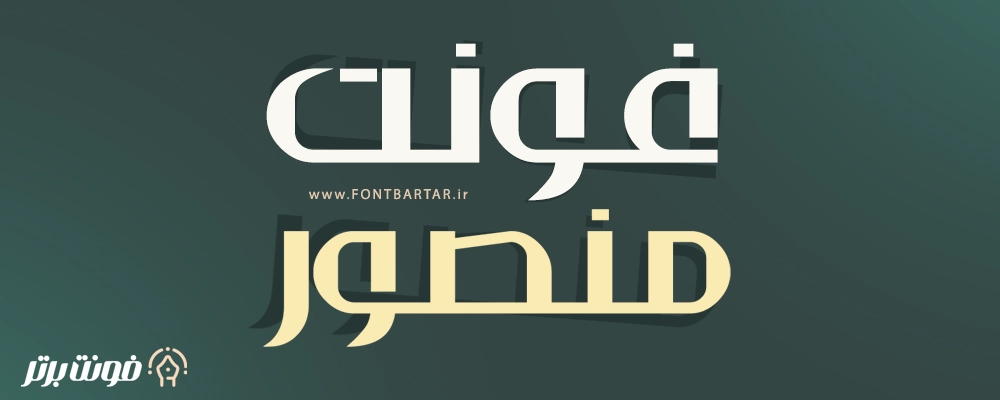
فونت جدید منصور | فونت فارسی شیک و حرفهای برای طراحی
معرفی فونت منصور
فونت منصور یکی از جدیدترین و جذابترین فونت های فارسی است که با طراحی مدرن و در عین حال خوانا، انتخابی عالی برای طراحان گرافیک، تولیدکنندگان محتوا، ناشران و کسبوکارهای آنلاین به شمار میرود. فونت لوگو تایپ فارسی با الهام از سبکهای مینیمال طراحی شده و ترکیبی از زیبایی، کاربردی بودن و نوستالژی مدرن را در خود جای داده است.
اگر به دنبال یک فونت فارسی حرفهای برای لوگو، پوستر، بنر تبلیغاتی، موشن گرافیک یا وبسایت هستید، فونت زیبا منصور بهترین گزینه برای شماست.
ویژگی های فونت منصور
- فونت لوگوتایپ طراحی مدرن و کاربردی
- مناسب برای لوگوتایپ و برندینگ
- وضوح بالا در نمایشگر و چاپ
- قابل استفاده در طراحی پوستر، جلد کتاب، وبسایت و شبکههای اجتماعی
چرا فونت جدید منصور بهترین انتخاب است؟
لوگوتایپ فارسی فونت منصور علاوه بر زیبایی بصری، از نظر سئو و تجربه کاربری نیز اهمیت زیادی دارد. استفاده از دانلود فونت فارسی در طراحی سایت یا محتوای بصری میتواند باعث افزایش نرخ کلیک (CTR) و جلب توجه کاربران شود. همچنین به دلیل خوانایی بالا، برای متون طولانی و تبلیغاتی بسیار مناسب است.
جمع بندی فونت منصور
فونت منصور برای چه نوع طراحیهایی مناسب است؟
این فونت برای طراحی لوگو، پوستر، تبلیغات، جلد کتاب، کارت ویزیت و حتی وبسایت گزینهای عالی محسوب میشود.